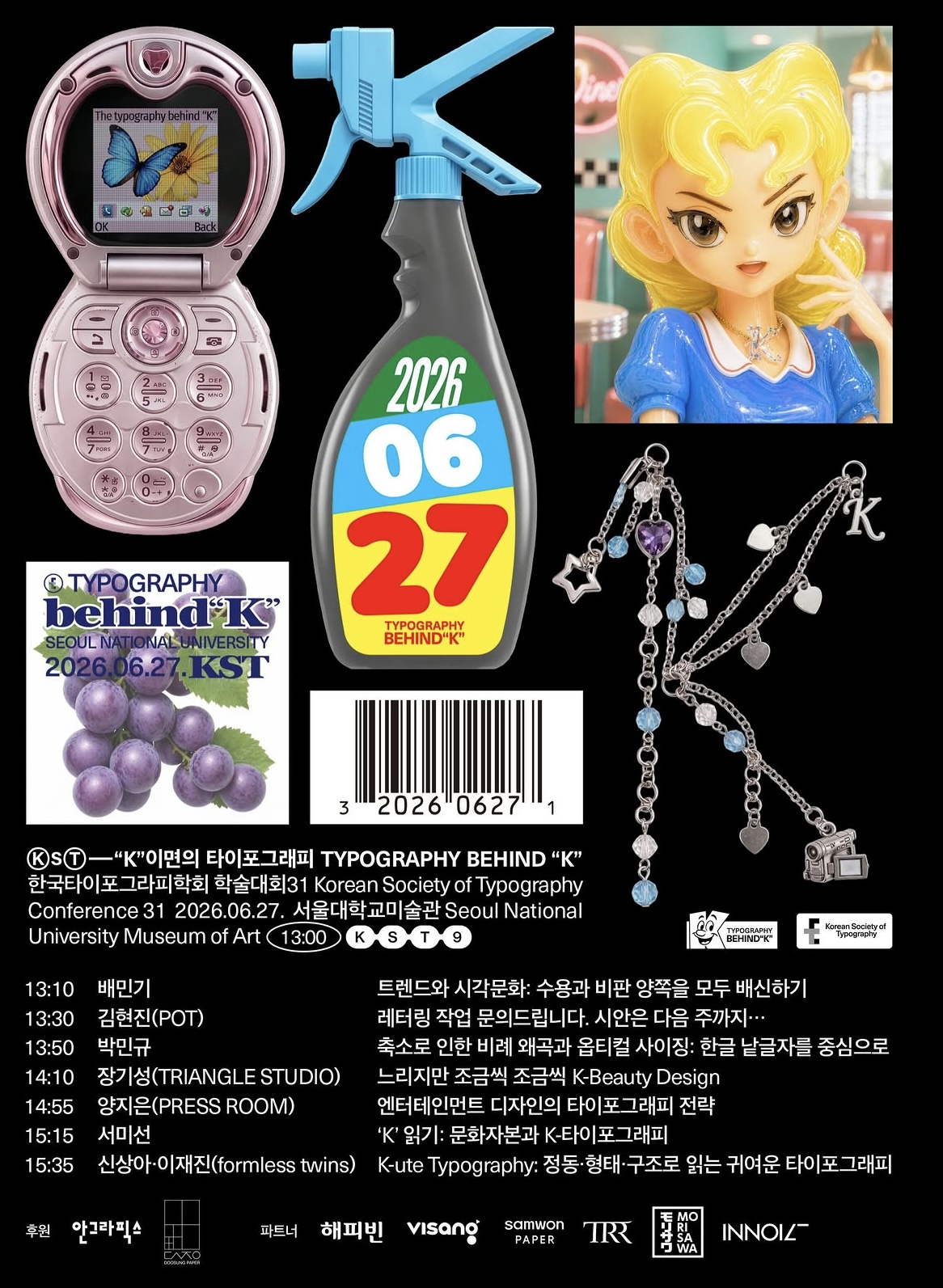
한국타이포그라피학회 《학술대회 31》
“K” 이면의 타이포그래피
“K”는 이름이 아니라 하나의 라벨입니다. K-Pop, K-Beauty, K-Food, K-Culture—이 접두어는 한국 문화를 하나의 이미지로 압축하고, 감수성을 유통 가능한 형식으로 변환하는 기호로 작동합니다. 그러나 이러한 표면적 기호 체계와는 별개로, 문자를 다루는 디자이너들의 실천은 보다 복합적인 층위에서 이루어져 왔습니다.
어떤 서체를 선택할 것인가, 한글을 어떻게 조형화할 것인가, K컬처를 구성하는 다양한 시각적 형식과 감각을 어떠한 구조와 리듬으로 조직할 것인가. 또한 책, 포스터, 브랜드, 디지털 미디어 등 다양한 매체 속에서 타이포그래피는 어떤 태도와 방법론을 통해 구현되는가.
이러한 선택과 실천은 “K”라는 이름으로는 쉽게 포착되지 않는 영역에서 이루어져 왔습니다. 그러나 바로 그 지점에서 우리의 문화는 축적되고 성장해 왔으며, 동시대 시각문화 역시 형성되어 왔습니다.
한국타이포그라피학회 제31회 학술대회 《“K” 이면의 타이포그래피》는 한국을 중심으로 국내외에서 활동하는 디자이너와 연구자들의 문자 탐구와 실천을 조망합니다. 그래픽 디자인과 타이포그래피 연구를 가로지르는 다양한 접근을 통해, 문자를 단순한 전달 수단을 넘어 하나의 구조이자 행위, 그리고 문화적 생성 방식으로 이해합니다.
이번 학술대회는 “K”라는 기호가 형성되는 과정과 그 이면에서 축적되어 온 다양한 실천의 층위를 함께 살펴보는 자리입니다. 동시대 시각문화 속에서 타이포그래피가 수행하는 역할과 가능성에 관심 있는 분들의 많은 참여를 바랍니다.
③ 연사. 배민기, 김현진(POT), 박민규, 장기성(TRIANGLE STUDIO), 양지은(PRESS ROOM), 서미선, 신상아·이재진(formless twins)
13:10 배민기 | 트렌드와 시각문화: 수용과 비판 양쪽을 모두 배신하기
13:30 김현진(POT) | 레터링 작업 문의드립니다. 시안은 다음 주까지…
13:50 박민규 | 축소로 인한 비례 왜곡과 옵티컬 사이징: 한글 낱글자를 중심으로
14:10 장기성(TRIANGLE STUDIO) | 느리지만 조금씩 조금씩 K-Beauty Design
14:55 양지은(PRESS ROOM) | 엔터테인먼트 디자인의 타이포그래피 전략
15:15 서미선 | ‘K’ 읽기: 문화자본과 K-타이포그래피
15:35 신상아·이재진(formless twins) | K-ute Typography: 정동·형태·구조로 읽는 귀여운 타이포그래피